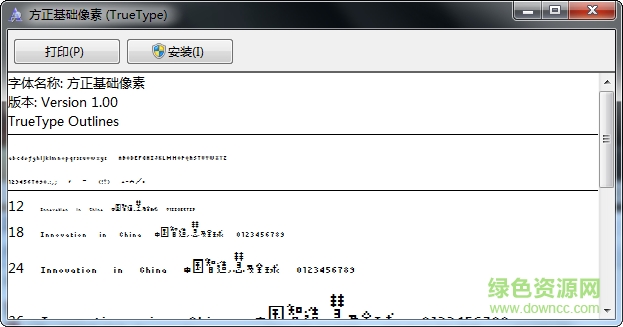
软件介绍 软件标签: 方正字体 像素字体 字体 方正基础像素字体是一款风格独特的中文像素字体,字形上和方正24、12等像素字有所不同,呈现凹凸有致的风格,需要下载这款字体的朋友拿走吧。方正基础像素字体安装方法方法一:控制面板/字体/文件/安装新字体;方法二:直接将字体复制到C:\WINDOWS\Fonts。小编提示本站所有字体资源仅供个人学习与参考,如需商业使用请到相关官网授权。 软件截图 上一张下一张(1 / 1) 安装详细截图 猜你喜欢 像素字体 手机像素游戏 像素字体 像素字体是一种非常有特色的字体,有中文也有英文,最主要的的特色就是它是由一像素的小方块组成的字体,这种字体在何种分辨率下都依然很想清晰,在PS中的署名、表情签之类的使用的都挺多的 查看更多>> 04b_03b 35KB/中文/5.0/下载 04b 21-普通 18KB/中文/3.3/下载 zpix字体 2.44M/中文/9.0/下载 fzxs12 gb1 0 245KB/中文/6.6/下载 可爱像素字体1.0 2.33M/中文/10.0/ttf版下载 方正基础像素字体 for mac 1.25M/中文/10.0/下载 手机像素游戏 手机像素游戏,大家可以理解为方块、颗粒游戏。因为游戏基本上是由方块或颗粒组成,看起来给人一种像素的感觉。像素游戏采用独特的怀旧画风,不想2D、3D游戏画面那样精美,但是其轮廓和色彩都非常清晰,角色造型也很卡通,这就是像素游戏的独特之处。 查看更多>> 我的世界钢铁侠模组免费 123.54M/中文/6.6/v1.75 安卓版下载 pixel studio汉化版 90.62M/中文/6.6/v4.94 安卓版下载 circle像素圆生成器 3.20M/中文/5.0/v2.2.36 安卓版下载 house像素之家 31.80M/中文/10.0/v1.0 安卓版下载 我的世界龙珠超模组整合包 513.09M/中文/6.0/v1.0 安卓版下载 其他版本下载 标题 大小 更新日期 下载 下载地址 电脑版 方正基础像素字体 免费版 点击报错 软件无法下载或下载后无法使用,请点击报错,谢谢! 关闭报错反馈 请描述您所遇到的错误,我们将尽快予以修正,谢谢! *必填项,请输入内容 本类最新 方正粉丝天下字体 官方版 方正雅珠体简体 共8款 fzlthjw-gb1-0 方正强克体系列字体 共8款 方正字体打包合集 for Mac 苹果电脑版 方正综艺繁体字体 相关文章 Photoshop字体安装使用方法和技巧 如何解决“无法新增字体”问题 Win 7系统安装字体方法 网页字体大小设置方法 怎么改网页字体大小 在Linux系统中安装字体的几种方法 windows7字体显示问题:打开某些程序的时候显示的是乱码 用户评论 热门评论 最新评论 发表评论 查看所有评论(0) 昵称: 请不要评论无意义或脏话,我们所有评论会有人工审核. 字数: 0/500 (您的评论需要经过审核才能显示)